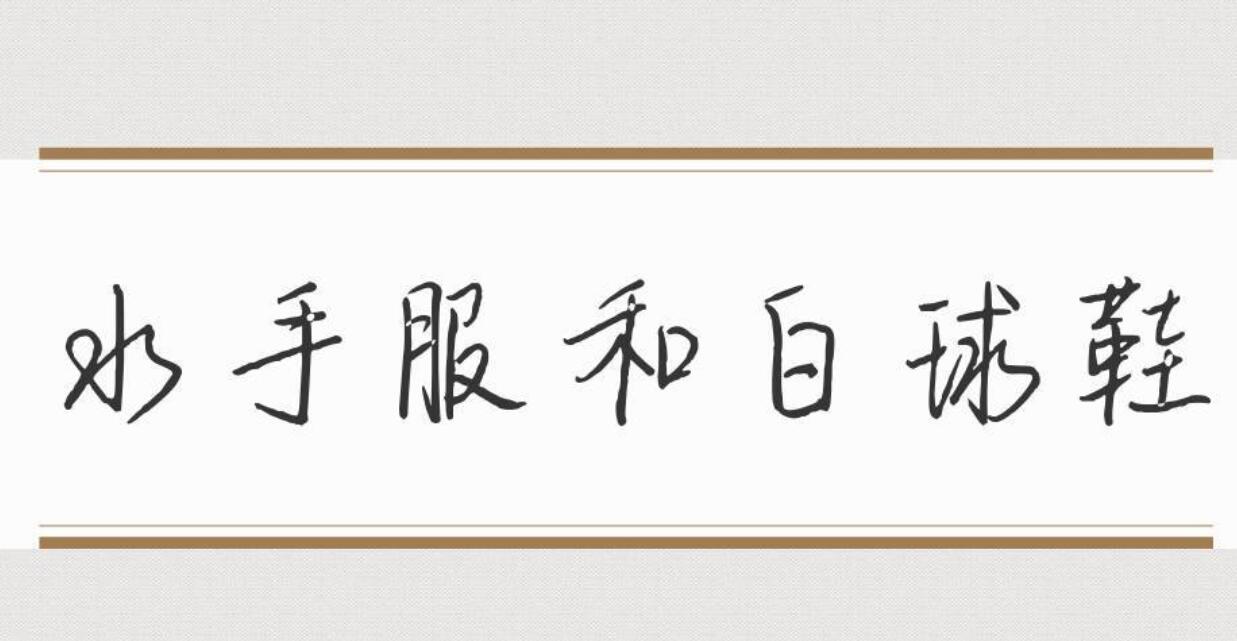
水手服和白球鞋是文道字庫(kù)推出的一款非常不錯(cuò)的藝術(shù)字體,連貫字跡顯得干練而不凌亂,清新簡(jiǎn)明,具有很好的視覺(jué)感,適合應(yīng)用于藝術(shù)設(shè)計(jì)、平面宣傳設(shè)計(jì)、網(wǎng)頁(yè)設(shè)計(jì),書法字帖等領(lǐng)域,歡迎喜歡冬日限定草莓字體的朋友前來(lái)下載使用。